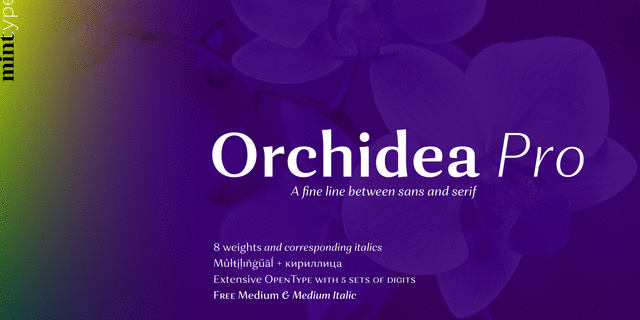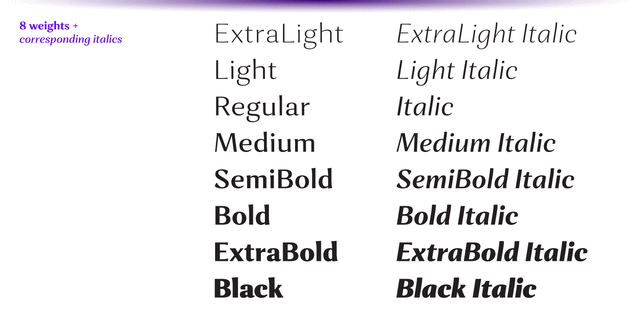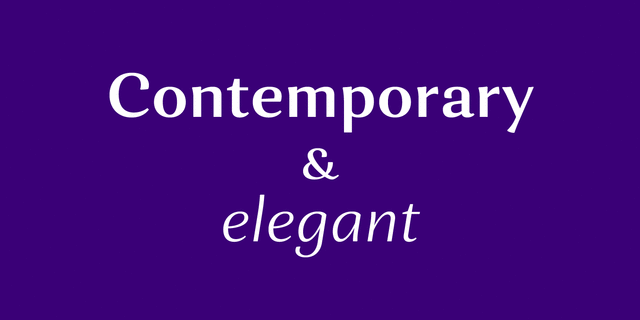
Orchidea Pro – это шрифт, балансирующий на грани между гротеском и антиквой. Так называемая ленточная антиква или антиква-гротеск, шрифт не имеет никаких засечек, но напоминает антиквы по конструкции и имеет однонаправленные концевые элементы, которые ускоряют чтение и создают особую различимость формы.
Такое решение создает современный, но элегантный шрифт, практически уникальный по текстуре, который существует в одном стилистическом пространстве со шрифтами с плавными засечками.
Orchidea Pro подходит особенно хорошо для использования в журналах, а также в брендинге косметических продуктов.
Шрифт имеет 8 вариантов насыщенности от сверхсветлого до сверхжирного + соответствующий реальный курсив. Каждое начертание поддерживает многочисленные языки на латинице, основные кириллические языки и содержит множество опен-тайп фич: лигатуры, капитель, 5 наборов цифр, 4 стилистических набора в прямых начертания и 1 в курсивном, дроби, индексы, различные знаки пунктуации, включая пунктуацию для капитального набора, а также языковые альтернативы.
Шрифт Orchidea Pro разработал и выпустил Андрей Константинов в студии Mint Type в 2017 году.